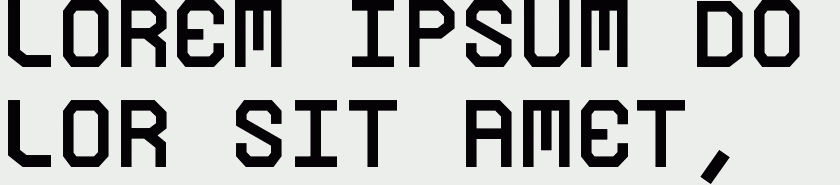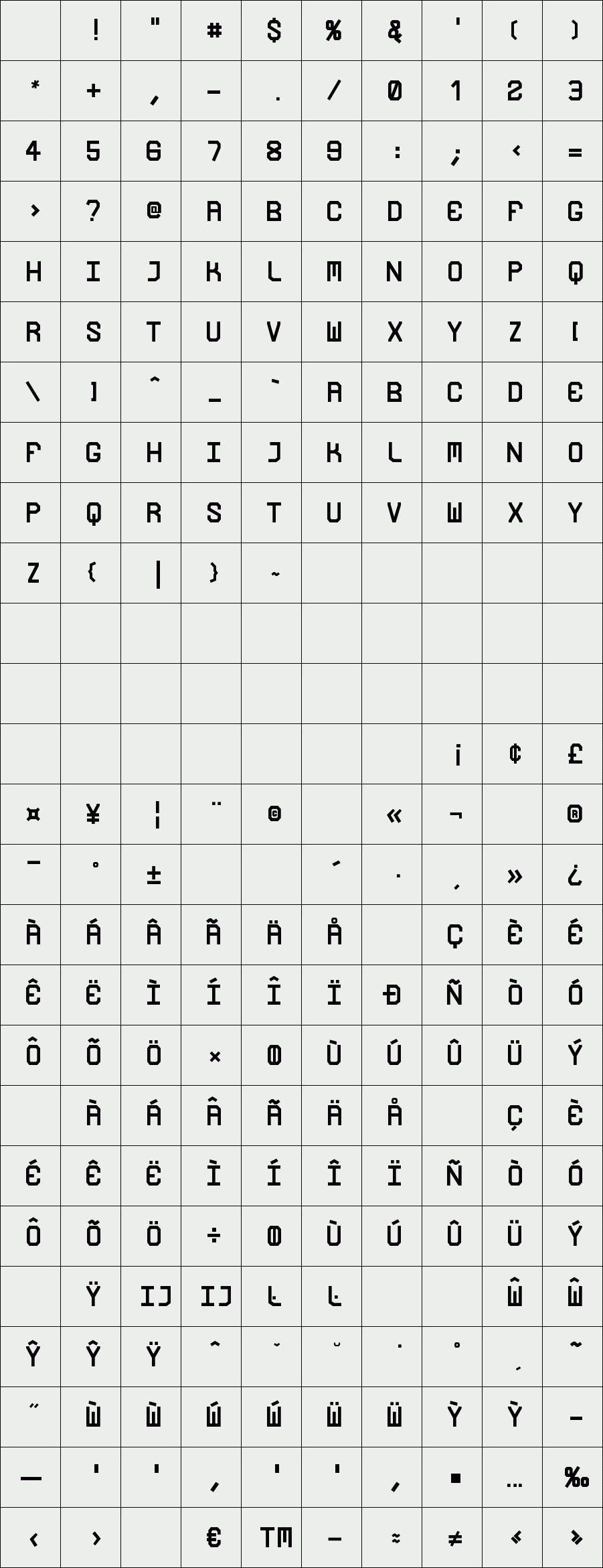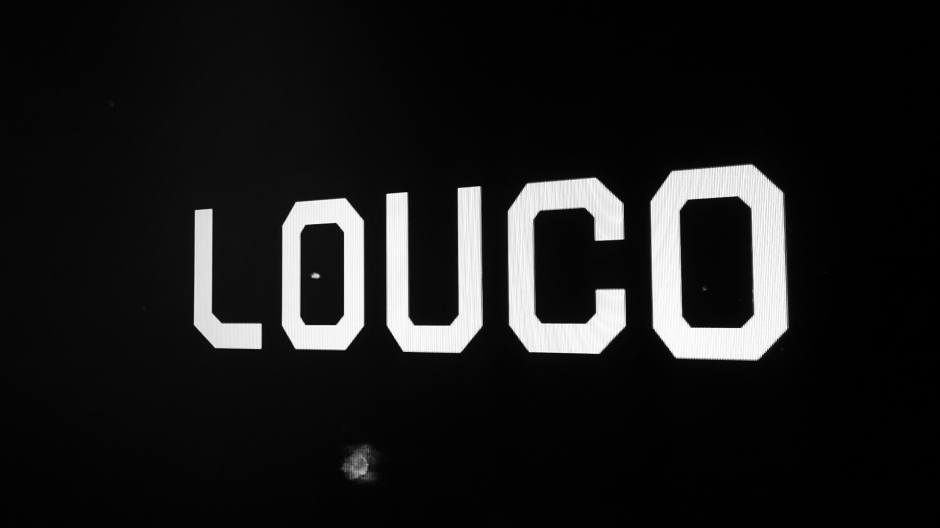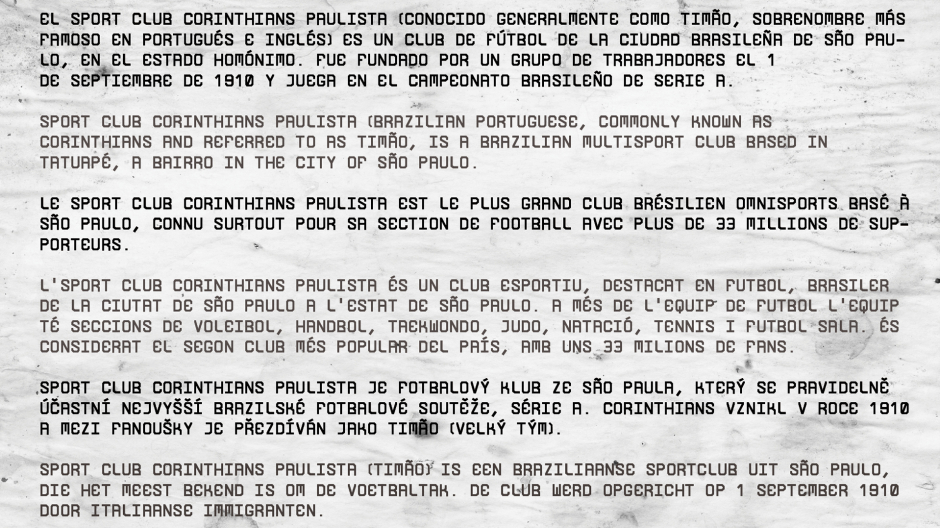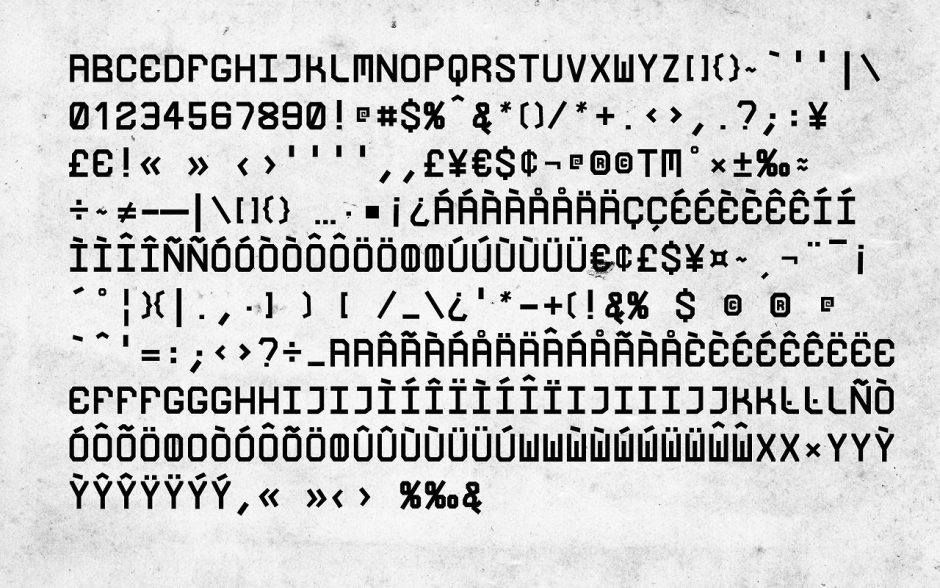
Louco
[PT] Do estádio mais longe, até o mais perto. Um bando de loucos, do Brasil até o Japão. A torcida que tem um time e que joga junto, empurrando e cantando. Tipografia Louco, inspirada nas faixas da torcida do Corinthians que são levadas para o estádio.
[EN] No matter how far away the team play, Corinthians’ crazies supporters follow their beloved team. From Brazil to Japan. A crowd that has a team and playing together with the players, encouraging and singing. Louco (Crazy) Type, inspired by Corinthians’ supportes who bring their words into the stadium.